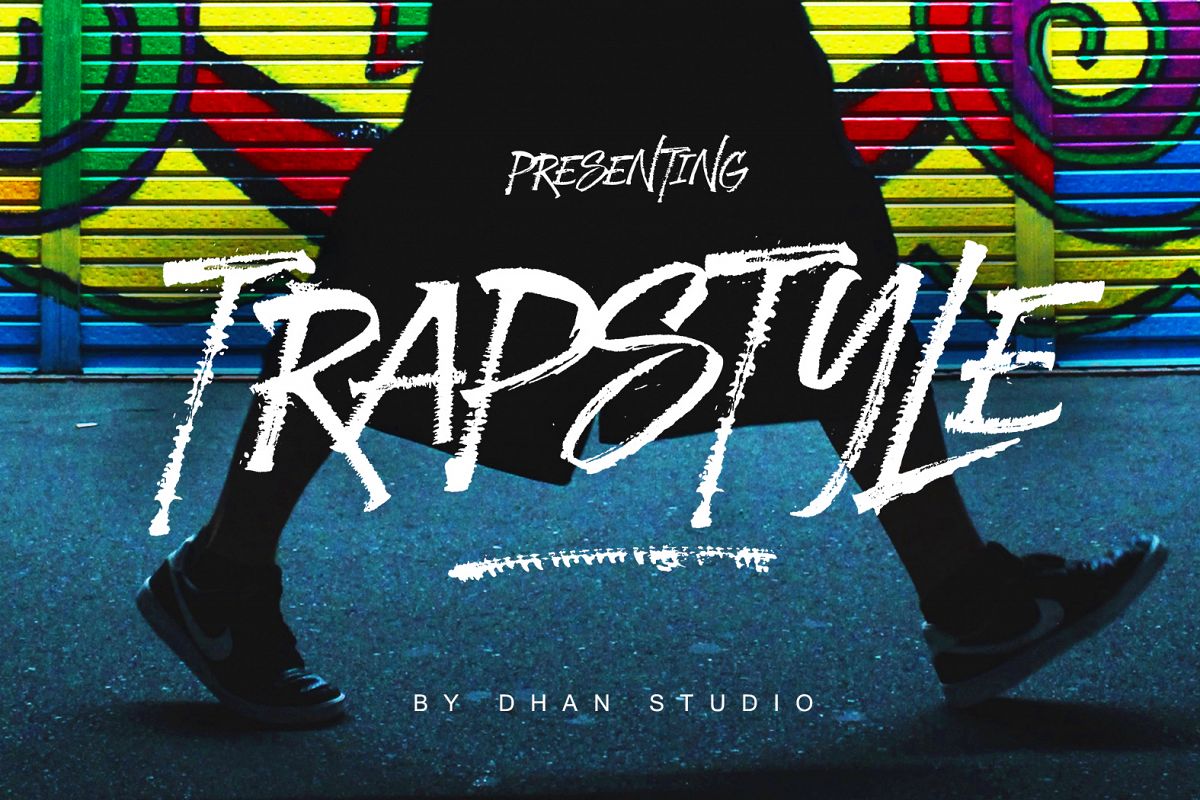
Trapstyle - Ruling Pen Font
TRAPSTYLE adalah tulisan tangan yang dibuat dengan Ruling Pen, alat ini dalam kaligrafi untuk tulisan ekspresif. font ini akan merobek teks Anda dengan aliran energi, dinamis, dan spontan yang tidak salah. Untuk membantu Anda membuat tampilan kustomisasi font tangan yang indah.
TRAPSTYLE dilengkapi dengan karakter, ligatur, huruf besar dan huruf kecil, tanda baca, angka. Juga termasuk bonus tambahan, iklan yang dirancang dengan sempurna untuk berita utama dan teks pendek. Tersedia untuk majalah, t-shirt, kemasan, logo, iklan, kutipan, branding, poster, editorial, sampul karya seni, film, situs web, dll.